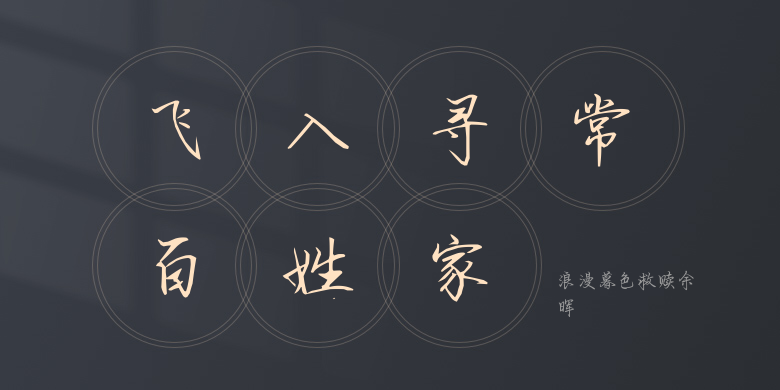
浪漫暮色救赎余晖
浪漫暮色救赎余晖,这款字体结构工整、笔画清晰,兼顾美观与易读性,适用于标题、正文、海报、包装、LOGO 等多种场景。字形优雅稳定,风格百搭耐看,适配日常排版与创意设计,让文字呈现更舒适、更具质感。浪漫暮色救赎余晖一笔一画,皆是细节,以均衡的比例、流畅的线条打造舒适视觉体验,字形端正大气,风格简约现代。无论是商业设计、品牌宣传还是日常排版,都能轻松驾驭,让文字更有格调与力量。浪漫暮色救赎余晖字体下载。